Логотип — неотъемлемая часть айдентики любого бренда. Все логотипы можно условно разделить на три большие группы: графические, шрифтовые и комбинированные. И если в первом случае ставка делается на символ, то в остальных немалую, а то и ведущую роль играет шрифт.
Он может быть модным и дерзким, красивым и изящным, современным и лаконичным. Главное — подобрать тот, который подойдет именно вам. В этой статье мы расскажем о том, как это правильно сделать, и выберем 15 лучших шрифтов для логотипа из коллекции TypeType, актуальных в 2025 году.
Какой шрифт использовать в логотипе: советы по выбору
Главная функция логотипа — представлять бренд в визуальном пространстве. Шрифт, который станет его основой, должен соответствовать следующим критериям:
- Соответствие стилю: логотип должен передавать общее настроение бренда;
- Узнаваемость: шрифт логотипе должен быть уникальным и запоминающимся;
- Разборчивость: буква, слово или фраза должна легко считываться, по возможности стоит выбирать простой шрифт для логотипа;
- Технологичность: важно, чтобы шрифт работал на всех платформах и отображался на разных устройствах.
Именно логотипу ваша потенциальная аудитория или будущие клиенты будут делать первые предположения о том, что из себя представляет ваш бренд. Поэтому стиль шрифта для логотипа должен соответствовать характеру продукта или компании. Универсального варианта для любого логотипа не существует. Удачный шрифт — тот, который использован уместно.
Приведем простой пример: представьте, что в логотипе магазина детской одежды используется, скажем, кириллический шрифт Izhitsa Cyrillic (вы могли видеть его в айдентике группы «Король и Шут»). Какие эмоции вызовет такой логотип?
Конечно, если это специализированный магазин, связанный со славянской тематикой , шрифт поможет рассказать об этой особенности и выделить бренд среди других. Но если компания выпускает повседневную детскую одежду, ожидания потенциальных покупателей либо будут обмануты, либо они просто не обратят на такой логотип внимания и не дойдут до этапа ознакомления с товаром.
Вот еще один пример: вообразите, что необычный дизайнерский шрифт использовали для логотипа официального государственного сайта. Скажем, это шрифт Oi от дизайнера Kostas Bartsokas, примененный для логотипа нотариальной конторы. Какой эффект вызовет подобное решение? Скорее всего, вы подумаете, что ошиблись с адресом сайта и портал вызовет у вас недоверие.
Совет: перед выбором шрифта изучите логотипы конкурентов. Выберите самые популярные шрифты для логотипов в вашей сфере, проанализируйте, какие эмоции они вызывают.
После того, как вы определитесь со стилем, стоит подумать об оригинальности. Похожие или даже одинаковые на первый взгляд гарнитуры могут различаться незначительно — например, прорисовкой всего нескольких символов. Однако такие мелкие детали помогут сделать ваш логотип одновременно узнаваемым и уникальным.
Совет: выбирая шрифт из визуально похожих вариантов, изучите именно те буквы и знаки, которые будут использоваться в вашем логотипе. Посмотрите, как они выглядят по отдельности и расставьте их в нужном порядке, чтобы увидеть, какой эффект они создадут в комбинации. Может случиться так, что литеры из изначально приглянувшийся вам гарнитуры не создадут нужного эффекта в логотипе.
Как много шрифтов следует использовать в лого
Логотип не должен быть перегруженным, поэтому лучше всего использовать минимальное количество шрифтов. Максимум — два или три, в идеале — один. Правило «чем проще, тем лучше» здесь точно работает.
Как сочетать шрифты для логотипов
Если вы все же решили миксовать в логотипе несколько шрифтов, важно делать это правильно. Комбинировать шрифты нужно так, чтобы они дополняли друг друга, а не «перекрикивали».
Здесь есть два варианта. Первый — комбинировать разные начертания из одной и той же гарнитуры. В этом случае гораздо проще не ошибиться со стилем.
Второй — создать шрифтовую пару. Сделать это сложно, четких правил по сочетанию не существует. Но есть готовые шрифтовые пары — например, в нашей студии такими являются TT Norms® Pro и TT Norms® Pro Serif. Подробнее о шрифтовых парах читайте в нашей статье.
Виды шрифтов для логотипов
Какие шрифты можно использовать в логотипе? Теоретически — любые, строгих ограничений здесь нет. Однако, учитывая вышеперечисленные советы, можно выделить следующие типы шрифтов, подходящие для логотипа:
- Антиквы — обобщенное название для всех шрифтов с засечками. Обычно их разделяют на четыре подкатегории: старостильные, переходные, новостильные и брусковые.
- Гротески — шрифты без засечек. Они также делятся на подкатегории — старые, гуманистические и геометрические гротески, неогротески.
- Брусковые шрифты — это подкатегория антикв, но с характерным отличием. Их можно узнать по мощным, массивным засечкам.
- Рукописные шрифты — группа шрифтов, которые имитируют рукописный почерк.
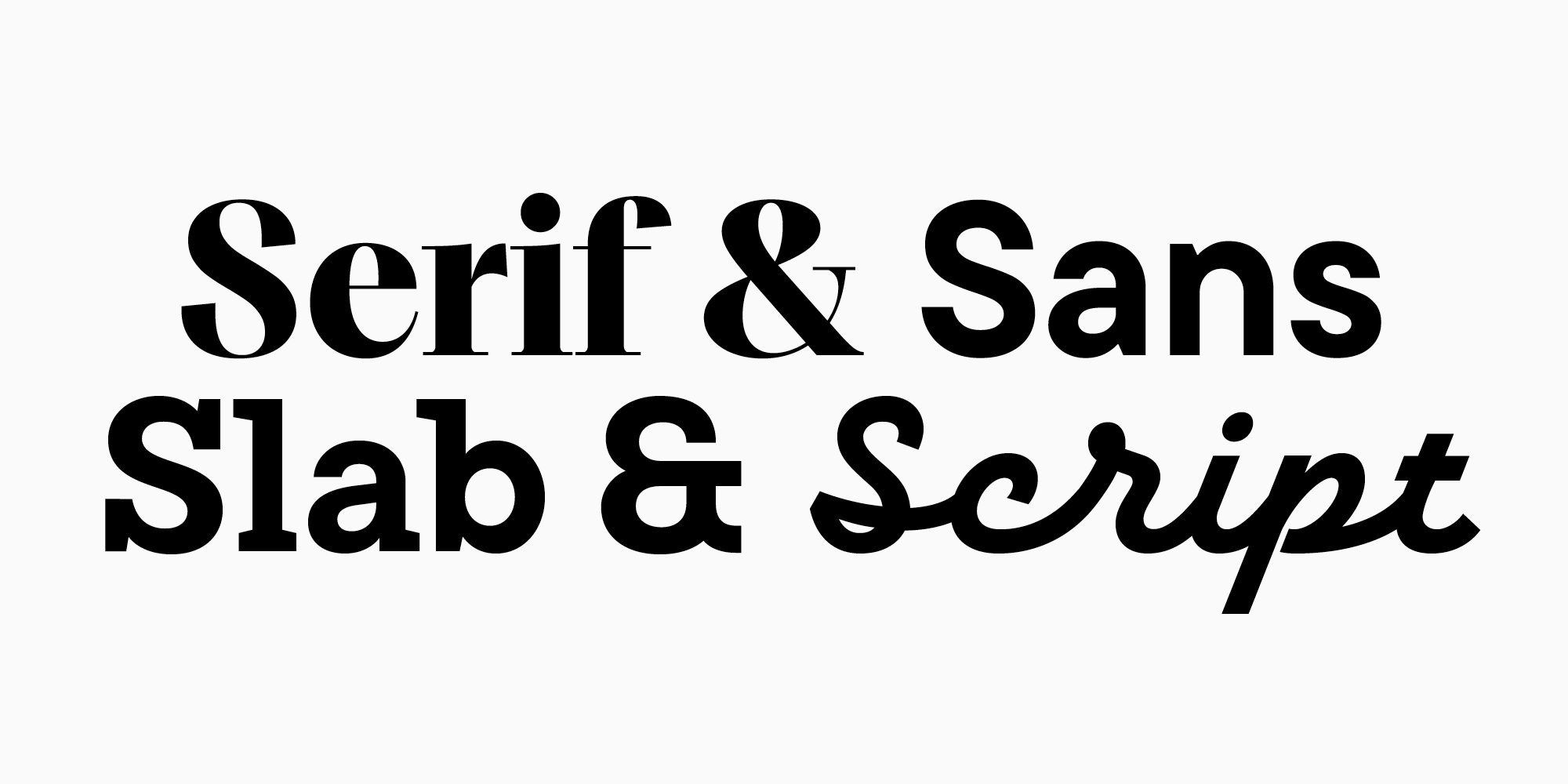
Лучшие современные шрифты с засечками для логотипов
Шрифты с засечками, или антиквы, чаще всего применяют для того, чтобы подчеркнуть статусность или показать изящество бренда, создать ощущение богатой истории или уважения к традициям. Однако сфера применения современных шрифтов из этой категории довольно широка.
TT Livret — актуальная антиква без эффекта «старины»
Гарнитура TT Livret — отличный пример современной функциональной антиквы. У этого шрифта одновременно изящный и спокойный характер, поэтому он легко впишется в логотипы разных брендов.
Современный и изящный TT Ramillas
Другой пример — шрифт TT Ramillas. Сфера применения у него более узкая, однако он тоже прекрасно приспособлен к современным реалиям и техническим требованиям. Данная гарнитура подойдет для логотипов, в которых нужно отразить премиальность и люксовость. Например, для бутиков одежды, парфюмерии или ювелирных украшений.
Мягкий и нежный TT Phobos
Пластичная акцидентная антиква TT Phobos поможет привлечь внимание к вашему логотипу, при этом эффект не будет навязчивым, так как шрифт обладает мягким, дружелюбным характером. Особое внимание рекомендуем обратить на начертание Stensil — оно идеально для логотипов. Шрифт TT Phobos отлично подойдет, в частности, для логотипов кондитерских или ресторанов.
TT Espina — выразительная и трендовая
TT Espina — дисплейная антиква, вдохновленная историей, но при этом современная. Это необычный шрифт, у которого много интересных деталей, так что логотип или фирменный знак с ним точно захочется рассмотреть. Но стоит учесть, что данный вариант подойдет для использования в крупном размере.
Самые красивые шрифты без засечек для логотипа
Шрифты без засечек, или гротески — наиболее универсальные шрифты. Благодаря простоте и зачастую нейтральности они могут применяться в разных сферах. С помощью шрифтов без засечек оформляются логотипы брендов одежды, логотипы сайтов или компьютерных игр — в общем, вариантов множество.
Бестселлер TT Norms® Pro
Один из самых популярных шрифтов нашей студии — функциональный геометрический гротеск TT Norms® Pro. Он удобен в использовании с технической стороны и универсален в эстетическом смысле. Подойдет практически для любой сферы — логотипов мобильных приложений, брендов одежды, СМИ, образовательных проектов и так далее.
TT Trailers — шрифт для яркого фирменного стиля
TT Trailers — яркий акцидентный гротеск. Это довольно интересный шрифт для логотипа, при этом применять его можно в разных тематиках. Изначальная версия гарнитуры создавалась специально для киноиндустрии, но обновленный вариант будет гармонично смотреться в логотипах журналов, ресторанов, пищевых продуктов и напитков, приложений и сайтов.
Стильный, модный, молодежный TT Travels Next
Если вы ищете модный шрифт для логотипа, обратите внимание на TT Travels Next. Это широкий акцидентный гротеск с привлекательными деталями. Он хорошо впишется в айдентику современных брендов.
TT Alientz Grotesque — инопланетный гротеск для необычных решений
Хоть гротески и считаются универсальными, среди них есть по-настоящему нетривиальные варианты. TT Alientz Grotesque из семейства TT Alientz — один из них. Сверхакцидентный, дерзкий, колючий — это выбор для тех, кто ищет крутой шрифт для логотипа. Гарнитура легко впишется в айдентику неформальных эпатажных проектов, желающих заявить о себе. Она поможет создать ощущение чего-то потустороннего, магического, экспериментального и нонконформистского.
Лучшие брусковые шрифты для логотипов
Брусковые шрифты при использовании в логотипах вызывают разные ассоциации: они могут быть как серьезными и основательными, так и яркими и привлекающими внимание. Сфера их применения также довольно широка, все зависит от конкретной гарнитуры.
Броский и динамичный TT Cometus
Для создания яркого и привлекающего внимание логотипа подойдет брусковый шрифт TT Cometus. Он массивный, но при этом пластичный и динамичный — логотип с таким шрифтом будет выглядеть современно, броско и уверенно. А плавные формы делают характер этого напористого шрифта вполне дружелюбным. Подойдет только для логотипов на латинице, не поддерживает кириллические шрифты.
Строгий и выверенный TT Rationalist
Если ваша цель — найти узнаваемый и универсальный, но при этом оригинальный шрифт для логотипа, решением может стать TT Rationalist. Эта гарнитура с классическим характером подойдет для многих сфер, при этом сделает логотип уникальным и современным.
TT Globs — актуальная база
В первую очередь отметим, что это еще одна гарнитура, которая не поддерживает кириллические языки, доступна только латиница. Если вам нужен шрифт для логотипа на английском, смело рассматривайте этот вариант. TT Globs — актуальный широкий шрифт, один из базовых в нашей коллекции. Сфера его применения очень широка.
Лучшие рукописные шрифты для логотипов
Рукописные шрифты, или прописные шрифты для логотипа могут использоваться для разных целей: они бывают небрежными и игривыми, строгими и элегантными. Однако все они хорошо подходят для того, чтобы придать логотипу эффект «рукотворности», передать ощущение локальности, показать, что в бренде есть что-то оригинальное и необычное.
Романтичный и игривый TT Lovelies Script
TT Lovelies Script разрабатывался на основе авторской каллиграфии. В результате получился уникальный шрифт — высокофункциональный и технологичный, при этом живой и местами непредсказуемый. Его главная особенность — неразрывность. Это настоящая находка для тех, кому нужен красивый, утонченный и нескучный шрифт для логотипа.
TT Knickerbockers Script
Противоположный по характеру шрифт — TT Knickerbockers Script, вдохновленный Нью-Йорком и его архитектурой. Монументальный, динамичный, с прямым написанием — он более строгий, но тоже поможет создать ощущение «крафтовости». Подойдет для многих сфер.
TT Polls Script — американская классика в стиле ретро
TT Polls Script из семейства TT Polls привычен глазу, такая форма часто встречается среди рукописных шрифтов. Он отсылает к классическому американскому стилю и создает ощущение ретро. Если грамотно использовать его в логотипе, эти особенности будут играть в вашу пользу.
Шрифты известных логотипов компаний
Для большей наглядности рассмотрим, какие шрифты для своих логотипов используют известные бренды. Здесь вы найдете еще несколько вариантов шрифтов TypeType, которые могут подойти и для вашего проекта.
Отметим, что многие компании используют для текстовых логотипов или в паре с фирменным знаком собственные корпоративные шрифты. К таким относятся, например, Uber (шрифт Uber Move), Apple (используют шрифт San Francisco), Cartoon Network (шрифт CN Bold).
Также логотипы известных брендов часто создаются на основе кастомного леттеринга. Такое решение можно увидеть, например, в айдентике Coca-Cola, Minecraft, Nickelodeon, Tesla и Google.
Зачастую компании используют для логотипов готовые шрифты или заказывают их специально для проекта.
Вот несколько примеров логотипов, разработанных на базе шрифтов нашей студии:
- В логотипе канала потокового видео новостей CBS News используется TT Norms® Pro, который мы уже упоминали ранее.
- Сеть ювелирных магазинов Adamas для своего логотипа использует шрифт TT Runs — широкий гротеск, отличающийся необычными пропорциями. Интересно, что изначально гарнитура разрабатывалась для спортивной индустрии, но сейчас используется гораздо шире. Это действительно универсальный вариант, рекомендуем взять его на заметку.
- TT Hoves Pro — еще один универсальный гротеск. Модифицированную версию этого шрифта можно увидеть в логотипе и на сайте крупной испанской телекоммуникационной компании Telefonica. В оригинальном же виде он используется в логотипе литовского государственного агентства Invest Lithuania.
А вот какие шрифты применяют другие известные бренды:
- Газпром — Helios Cond;
- Почта России — DG Roslyn Gothic;
- Авиасейлс — Stapel от студии «Паратайп»;
- Роснефть — Europe Extended Bold от Type Market;
- Wildberries — Montserrat;
- В новом логотипе «ВкусВилл» — фирменный шрифт от студии Letterhead.
Заключение
Итак, мы собрали коллекцию из более чем 15 шрифтов для логотипов, актуальных в 2025 году. Вы можете опираться на этот список и наши советы при создании своего фирменного знака.
Однако помните, что любые правила условны и что-то новое создается там, где рушатся рамки. Изучайте шрифты, развивайте визуальную интуицию и не бойтесь экспериментировать!